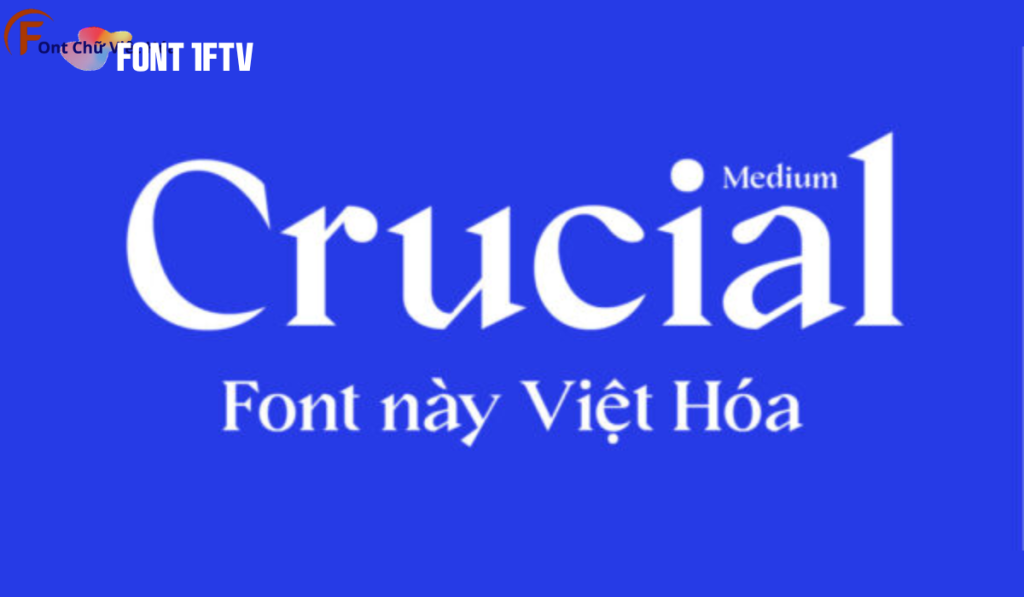
Font 1FTV Crucial Medium
Tác giả: 1FTV
Bộ Font: 1FTV
Kiểu chữ: Sans-serif
Độ dày: Medium
Font 1FTV Crucial Medium là một font chữ độc đáo, thuộc bộ 1FTV, nổi bật với phong cách sans-serif hiện đại và các đường nét mạnh mẽ, cá tính. Thiết kế của 1FTV Crucial Medium tập trung vào sự rõ ràng và dễ đọc, đặc biệt phù hợp cho các thiết kế đòi hỏi tính thẩm mỹ cao như poster, logo, và tiêu đề. Với tỷ lệ chữ cân đối và các đường nét đậm, font này tạo ra ấn tượng thị giác mạnh mẽ và giúp tối ưu hóa không gian trong thiết kế. Font này cũng đã được Việt hóa, mang đến sự linh hoạt và tiện dụng cho các dự án thiết kế bằng tiếng Việt.